Ein Vorurteil in der deutschen Designszene lautet: Werber können keine Plakate. Das stimmt nicht. Ich bin sogar gegenteiliger Auffassung. Weil viel mehr Plakate von Werbern als von Grafikdesignern geschaffen werden, und weil diese sich tagtäglich auf den Straßen »verkaufen« müssen, entstehen in Agenturen wahrhaftig plakative Plakate. Das klingt jetzt wie »weißer Schimmel«, aber so lange man mit unplakativen Plakaten massenhaft unter die 100 Besten Plakate* im Land kommt, muss ich das eben mal doppelt gemoppelt formulieren. Kein Art-Direktor käme auf die Idee, kommerzielle Plakate mit siebgedrucktem Zierrat, tiefschürfenden Metaphern oder mikrotypografischen Sperenzchen zu inszenieren. Es sei denn, man gestaltet sie für die eigene Wand, oder die des Auftraggebers (zum Beispiel einen Theater-Intendanten) … oder einen Designwettbewerb.
Die oben abgebildete Plakatserie von Jung von Matt Elbe für den Hamburger Verein Jüdischer Salon am Grindel e. V. widerspricht gleich mehreren Vorurteilen. Wahrscheinlich ist sie auch für einen Wettbewerb gemacht, OK … trotzdem ist sie plakativ, zugleich gestalterisch sowie typografisch raffiniert und sie funktioniert.
* Nichts gegen den Wettbwerb, und weiß um das Bemühen der Veranstalter, die Werber anzusprechen … die einfach viel zu wenig einreichen. Aber der Name »100 Beste Kunstplakate« wäre auch in diesem Jahr wirklich treffender.
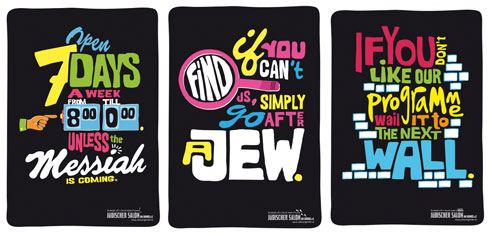
hmm, wenn ich mir die webseite des vereins so anschaue, kommen mir zweifel, dass es sich dabei nicht doch wieder nur um eine idee von jvm handelt, die im nachhinein durch den passenden kunden geadelt wurde und nur dazu dient als wettbewerbsbeitrag eingereicht zu werden. zum beispiel bei den 100 besten P’s. :)
gefallen tun sie mir aber. und jürgen GEMACHT hat sie sicher ein grafiker. sowas können werber nicht, dafür sind die damen und herren viel zu viel damit beschäftigt den kopf beim denken festzuhalten. :) ja ich weiss das das böse war. :-D
was die 100 besten P’s angeht, gebe ich dir recht. die »produktplakate« von werbeagenturen fallen auf und raus im positiven sinne. (so jetzt können die werber wieder die köpfe in die hände, ihr wisst schon. :-D)
Was ihr beschreibt ist für mich der Unterschied zwischen einem Poster und einem Plakat.
Ums mal ganz blöde zu sagen: Jazz in Willisau macht Poster, Mercedes Plakate. Ich finde, ein wirklich guter Designer sollte beides können.
Nice – aber ich gebe Thomas recht: Das ist gemacht für ADC-Nägel. Obwohl es für den Klienten sicher nett ist, wenn eine Monster-Werbeagentur auftaucht und für dich – billig oder umsonst, hauptsache Golden Idea, arbeiten will, ist es langfristig aus meiner Sicht eine traurige Angelegenheit. Zum einen scheint es also so zu sein, dass für die großen Kunden (und in der realen Werbung, nicht Sachen, die man hinten aufs C4 der Beef setzt ;-)) keine gute Arbeit zu machen ist. Zum anderen verzerrt es den Markt. Nicht nur, weil für uns kleineren Designbüros solche Jobs wegfallen – und ich rede da als Betroffener (Konzerthaus Dortmund) -, sondern auch, weil die Agenturen hier Arbeiten produzieren, die für das, was sie FÜR GELD machen nicht repräsentativ sind. Im Grunde also eine Art Lüge und natürlich auch die Illusion: So gut KÖNNTEN wir sein, aber die moneybringer lassen uns ja nicht.
Es ist ein bisschen so wie McDonalds, die mit etwas Salat so tun, als wären sie der Wellness-Foodanbieter schlechthin… aber trotzdem weiter Supersize-Burger anbieten :-D. Das ist schlecht für das Image echten Health-Foods und letzten Endes einfach nicht ehrlich.
Nur steckt halt nichts dahinter, wie ein Klick auf die Site beweist, die NICHTS mit der Kampagne zu tun hat – offensichtlich ist es nicht wichtig, einen Auftritt aus einem Guß zu produzieren, sondern nur ein Medium zu shanghaien. Dem Klienten hilft das nur leider wenig, wenn nach tollen Plakaten eine maue Site kommt, erst hui, dann pfui – da frag ich mich: Ja, was denn nun. Wer will sich da produzieren? Der Klient oder die Agentur. Und wir alle wissen: Der Job ist, DEN KLIENTEN zu verkaufen, nicht uns selbst. Das passiert hier aber nicht, es ist also das GEGENTEIL von gutem Design, so sorry.
Das also definitiv hier keine Strategie erzeugt wird, keine langfristige Wertschöpfung und Markenarchitektur entsteht, sondern nur Maximum Bang For Bucks angesagt ist, und oft Praktikanten-Ideen dem möglichst passenden Klienten aufgebuttert werden (wobei die Ideen nie so gut zusammenpassen, dass ein ganzes daraus wird…), ist das Doofe an der Sache. Macht Gute Arbeit da, wo es sich lohnt, überzeugt die großen Tiere von euren Ideen, nutzt eure Größe für diesen Zweck. Aber einerseits öde Autowerbung und andererseits dann visuell Potemkinsche Dörfer bei Kreativkunden, das ist keine echte Strategie, außer eben wenn es um Awardshows geht :-D.
Abgesehen davon erinnern mich die Plakate aber mal massiv an Milton Glaser. Dazu passt auch, dass es auf Englisch ist. Die SITE aber ist auf Deutsch. Was – Deutsch war zu uncool? Warum die Plakate nicht auf Deutsch sind – oder richtig gut wäre Jiddisch gewesen, immerhin eine fast vom Aussterben bedrohte und extrem großartige «Sprache» -, erschließt sich mir nicht. Euch? Verpasse ich einen Gag?
100 beste Plakate – fand ich auch, Jürgen. Mir haben nur ein zwei Plakate gefallen, und beim meisten fand ich irritierend, dass es Selbstauftrag war oder Uni-Veranstaltungen. Man sollte es dann ehrlich zu einem Studentenwettbewerb erklären und fertig. Dass kommerzielle Plakate – wir sitzen gerade an so einem Fall – einfach mehr kommunizieren, mehr Kompromiss haben, weniger feingeistig sein können (damit sie im Straßenverkehr noch funktionieren), ist halt eine Tatsache.
Und: Ich habe noch nie für ein Theater ein Plakat gemacht, dass der Intendant für seine Wand will. Da wird längst extrem auf Marketing und messbaren Erfolg (Abo, Ticketumsatz) geschaut, mitunter vielleicht sogar zu sehr, befürchte ich, denn gerade Theater sollte ja nicht unter reinen Effizienzaspekten stattfinden. Aber von 2001 an hab ich noch kein Kunst-um-der-Kunst-Willen für ein Theater machen müssen oder dürfen, ganz und gar im Gegenteil.
Coole Typografie. Erinnert mich an den Kanye West Videoclip von “Good Life”.
tolle sache nur sind diese plakate -aus typografischer sicht – ein plagiat des illustrators parra aus amsterdam.
sorry. checkt es ab. google: parra amsterdam